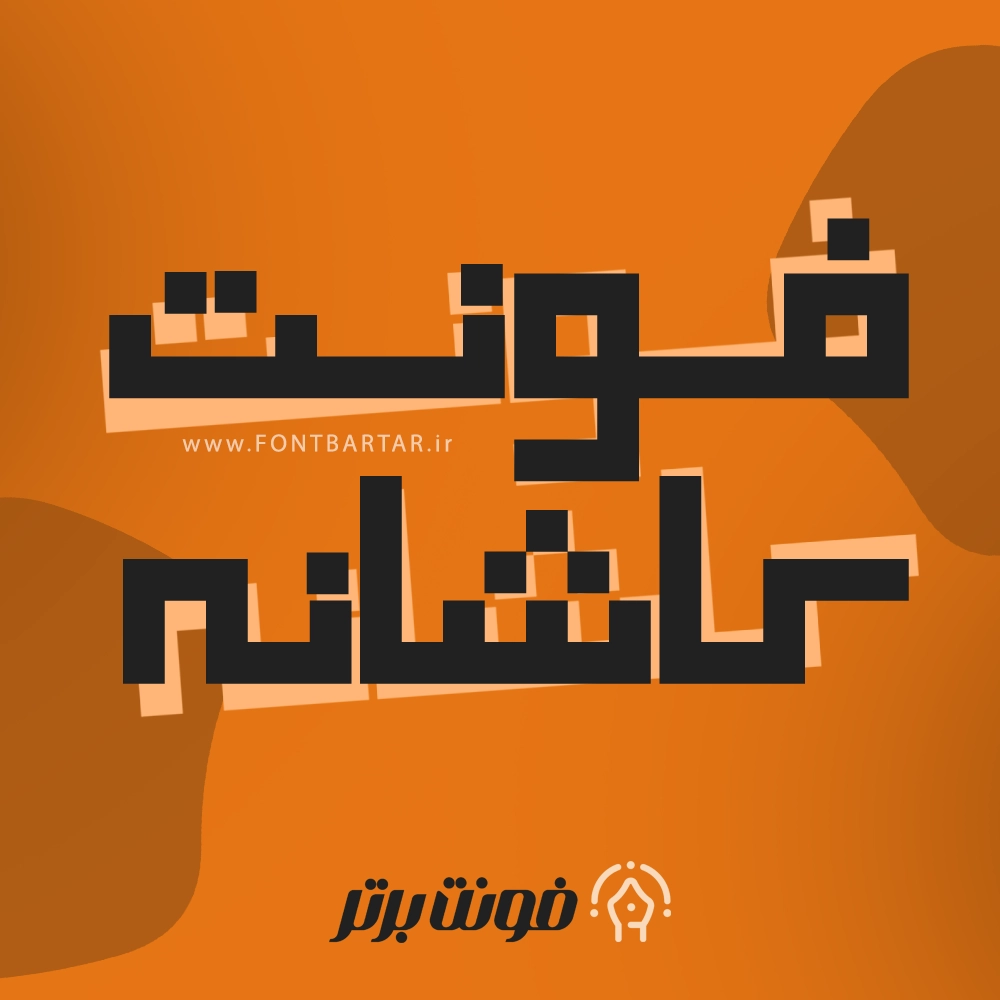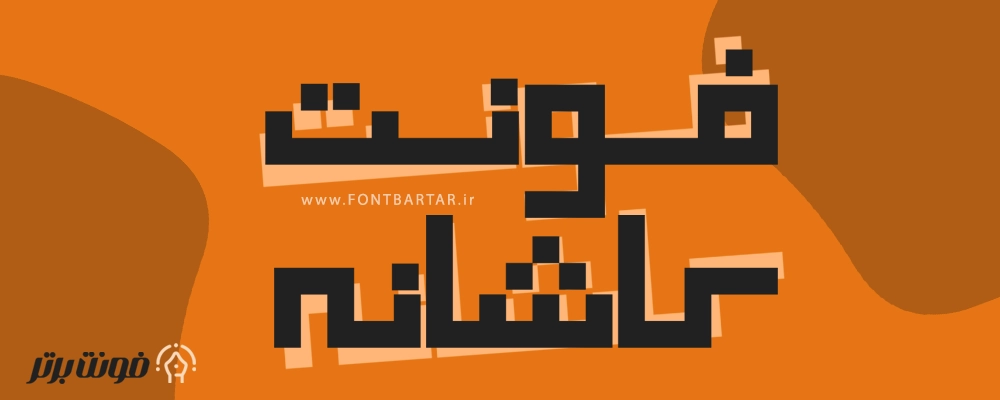
فونت کاشانه
Font Kashane
فونت کاشانه – ترکیب قدرت و سادگی در طراحی فارسی
فونت جدید کاشانه یکی از جذاب‌ترین فونت‌ های فارسی مدرن است که با الهام از ساختارهای هندسی و ضخیم طراحی شده است. فونت جدید برای اینشات مناسب طراحانی است که به دنبال فونتی قدرتمند، خوانا و متفاوت برای پروژه‌های تبلیغاتی خود هستند.
💡 ویژگی‌ های فونت جدید فارسی
• طراحی هندسی با ساختار مربعی و ضخیم
• مناسب برای استفاده در تیتر، پوستر، لوگوتایپ، بنر و کاور موسیقی
• هماهنگی کامل با فونت‌های فارسی و انگلیسی مدرن
• خروجی زیبا در محیط‌های طراحی مانند Photoshop، Illustrator و Canva
• خوانایی بالا در سایزهای بزرگ
🎨 کاربردهای فونت کاشانه
1. طراحی لوگوتایپ‌های فارسی با هویت قوی
4. ساخت بنر و پوستر تبلیغاتی
5. تایپوگرافی در شبکه‌های اجتماعی
6. طراحی جلد کتاب یا آلبوم
7. استفاده در پروژه‌های برندینگ
1. فونت کاشانه برای چه نوع طراحی مناسب است؟
فونت کاشانه برای طراحی‌های تبلیغاتی، تیترهای گرافیکی، لوگوتایپ و کاورهای موسیقی بسیار مناسب است.